一.雅黑设计理念
雅黑字体是为微软公司设计的屏幕显示汉字。它具有个性独特、结体优美、识别性强、块状效果好、显示清晰等优点。在当今数字化时代更是用途广泛。这副字可以说是科技进步的产物,是人类社会的需要,在设计上也有所突破。
首先打破传统结体方式,采用大字面设计,字怀放开,增大内白,使文字方正,布白匀称。由于字体中宫放开,使文字的适用性也随之增强,不但适合小级数文字的使用,更适合屏幕显示。
在笔型塑造上去除“喇叭头”。为防止文字笔划缺乏美感、没有精神,在撇、捺、点、勾的处理上使其粗细有略微的变化,使之富有弹性。
在制作上,力求精良,笔划间尽可能少搭笔,使文字清新、爽朗、易读。
追求字体的整体形式美,强调文字设计的审美性和文化性,朴实大方,典雅端庄。
下面从字体设计理论方面与实际字体应用的角度来阐述一下雅黑是用什么方法和字体设计技巧来完成和完善设计目标的。
二.按用途来设计字体
1.字体设计类型
字体设计可细分为平面美术字体设计和印刷“活字”设计。在这所要谈的字体设计是指在印刷“活字”范畴内的字体设计,主要研究字在缩小后的清晰度、可读性以及整体效果。在字型的处理上它不能象美术字和书法字那样,可以无视大小地尽情抒发情感,而要受到一定规矩的约束,讲究共性和个性的关系,来达到一种机械的美观。这种设计也是一门比较冷僻的视觉艺术。近年来,随着科学技术的不断发展,印刷“活字”设计又可分为出版印刷用字设计和屏幕显示用字设计这两个大类。
雅黑是属于屏幕显示用字,设计时更要注重研究字在低分辨率下的清晰度和可读性,尽可能做到小字号显示时的清晰易读,要达到这一目标,关键在于设定字面大小、笔型塑造和严谨合理的结构处理……。
2.字面大小的含义
我们有必要先来搞清楚两个不同的概念:“字面大小和字身字面比”。字体设计专用方格都有两个方框,外框称字身框,内框称字面框。
图1
字面大小:“就是在字面框不变的情况下,可以把字设计成大小不同的字,大字称字面大,小字称字面小。”
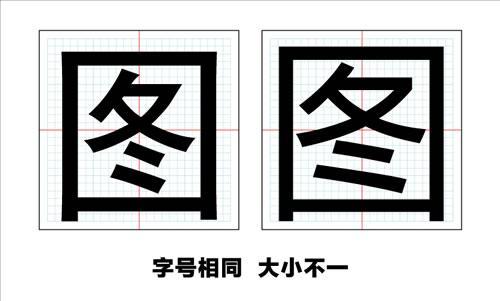
图2
字身框和字面框之间的距离就是半个自然字距。能正确地运用好他们之间的关系,是字体设计的基础。
字身字面比:“简单说就是在字身框不变的情况下,两者之间的百分比值,比值大字就大,比值小字就小,说白了就是把字放大和缩小。”
图3
现在有许多用户,为了能挤排,图省事,不惜把字缩小,造成字与字距之间的关系失衡。这样使用,即使有再好的字体也排不出完美的版面来,这是非常不科学的用法,与其这样,还不如缩小字号来用显得完美。
3. 字面的可测量大小和视觉大小
字面大小又可分为可测量的字面大小和视觉上的字面大小。已故字体设计大师谢培元老师在1962年归纳总结的“第二中心线”理论已表明,汉字由形声组合的字都是可以测量的,形旁和声旁这两个部件的中心距离越大,字面就越大,反之,字面就越小,我们只要测量这两个部件的中心距离就可以得到相应的字面大小值。同时,这也是控制整副字大小的有效工具。
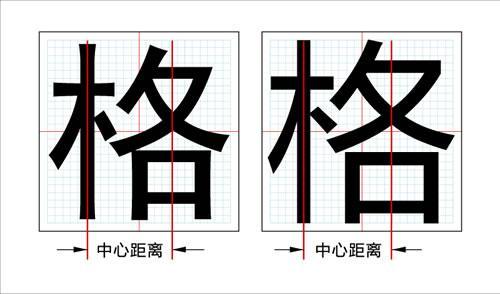
图4
雅黑在保持文字个性的基础上,尽可能的扩大形声这两个部件的中心距离来增大字面。同时,运用这种方法使得80%以上的字,大小保持一致。对于那些不能测量的字和一些易见小的字,雅黑又是如何处理呢?
字如从几何形角度来看,汉字形状众多,最典型的可分为四种类型:“方形、圆形、三角形和菱形”,从面积上看方形最大,菱形最小,要想把图形面积变得一样大小,就必须按菱形大小走,这样设计出的汉字才能在视觉上保持一致。
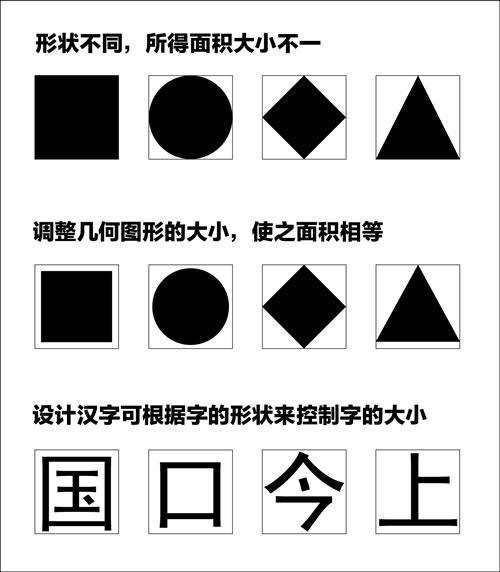
图5
要想做大字面的字,我们首先要考虑面积最小的菱形,那么,怎样才能把菱形字做大?很简单,只要适当调整改变菱形的形状,那么,我们就能得到比原来菱形面积大的形变图形,用这种方法来设计,就可以得到在视觉上比原先字面大的字。
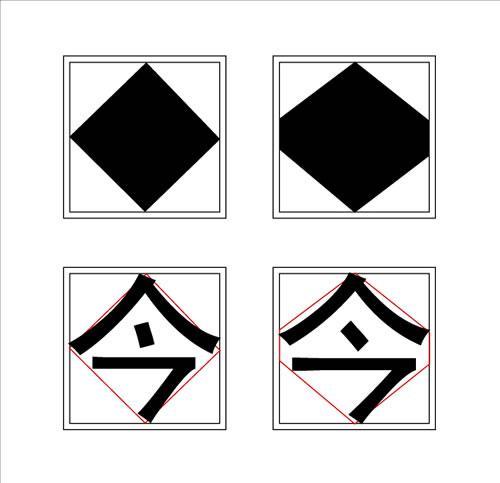
图6
雅黑在设计初期就是用视觉大小这种方法来定字面大小的。
4. 字面大小和屏幕显示的关系
字面大小和屏幕显示又有什么关系呢? 为了说明问题,用少点阵图来比较说明。
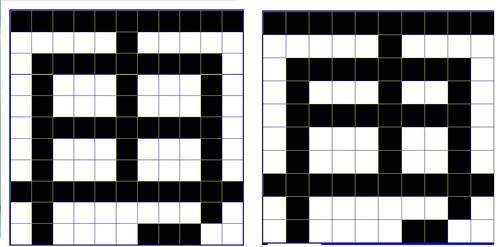
图7
从上面两图比较中我们可以看出,左图字面大,占像素多,内白均匀舒适、清晰易读。右图字面小,占像素少,因此,内白不匀称、识读效果变差。
雅黑设计时考虑到这一因素,不但采用大字面设计,同时,在字距较合理的范围内调大了字身字面,多争取到了每一点宝贵的像素,为小字号使用的清晰易读奠定了基础。
5. 去掉影响屏幕显示效果的“喇叭”口
现用黑体字的笔锋过大,成喇叭状,我们戏称为“喇叭头”或“喇叭口”。传统手写的黑体本应没有这么大的“喇叭头”,只稍微有点笔锋。那么,这“喇叭头”又是从何而来?有两个原因,第一,可能是个别写字人员认为喇叭口稍大些精神,故意写大些,第二,在把照相字模版的字翻制成电脑字库时,做字人员在不明白黑体字应有笔型的情况下,把原本制作照相字模版时,为防止在拍照缩小的过程中笔划变得虚弱、变圆走型而装上的“小辫”给融进了笔划,形成现在这样的“喇叭口”。
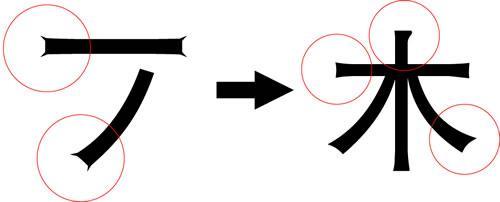
图8
过大的喇叭头,不但失去了黑体字应有的品格,在屏显时,“喇叭头”能在笔划两头多出一块,如果两笔离得较近,头就有可能连上,使笔划交代不清,可读性变差。
图9
雅黑属无装饰风格的字体,少了不必要的累赘,自然避免了这类问题的出现,使文字清晰易读。
三.雅黑设计中的要点
1.雅黑是根据我在90年代初期设计的黑体字库系列样张改进设计的。
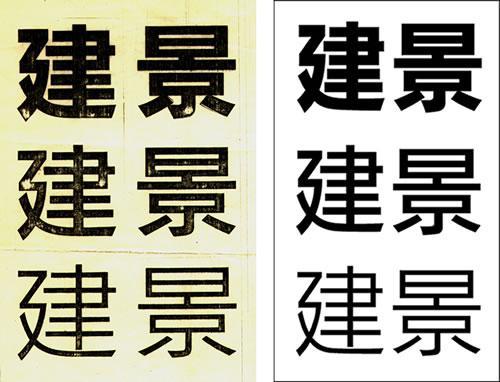
图10
从上述样张中可以看出,字体符合屏显字体的基本要求,字面大,无“喇叭头”,属无装饰风格的字体,可以作为雅黑的设计基础来改进提高。
2.雅黑设计上主要改进了字的粗细,“钩”的僵硬和“八”字点的写法,使其符合规范要求。同时,更注重线条的刻画,使其柔和挺拔富有弹性。
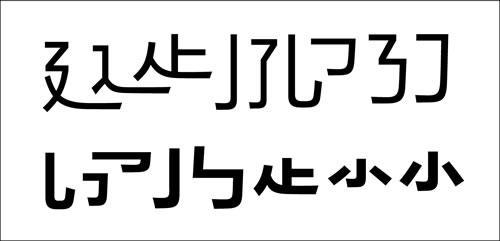
图11 部分笔划笔型图
3.为了使正文字的阅读效果更好,对所有的口和带框的部件加“脚”,也就是口下面出头,其目的是为了给眼睛以适量的刺激,来提高阅读速度,这是正文用雅黑设计的一次新尝试。
图12 口和带框的部件加“脚”
4. 为适合屏幕显示用,在字结构的处理上“计白当黑”,严格控制“白”在各部位所占的比例,使其舒朗匀称。
图13 黑白处理示意图
这种处理方式不但使字稳重大方,而且使字撇捺舒展、飘逸潇洒、富有姿态。
5. 采用独创的手法对笔划进行特殊处理,减少交错连笔处的黑度,使字的整体灰度更好,更清晰,更适合屏显。
图14 特殊笔划处理示意图
6.避免笔划交代不清,粘连过多
图15
这些字笔划交代不清,粘连过多,既降低了识、读的速度,又有错字嫌疑 。雅黑在设计时就尽量避免这种问题的发生。
图16
四.笔划粗细与结构、留白、重心之间的关系
这是活字设计中的一个综合问题,并非一朝一夕就能掌握的,它不但对字的个性要有深刻的理解,而且还要具有非常敏锐的观察力。做字的过程其实就是练眼的过程,眼睛练“凶”了,字自然越做越好。
下面通过调整统一字体的粗细,来了解笔划粗细与结构、留白、重心之间的关系。为了更好的说明问题,便于理解,选用多笔划和少笔划的粗体字为例。
图17
1 调整字的粗细,使之成为一个整体
这两个字一粗一细,视觉上看是两款字,粗细调整不当。首先,把细的“體”字加粗,使两个字的视觉粗细一致。
图18
2 字的内白影响字的重心
“體”字在加粗后,虽然在粗细上合适了,但是,看着还不舒服,仔细分析一下原因,问题在于内白,各部件的重心位置欠妥,骨字重心偏高,曲、豆重心偏低,使得互相间的呼应性、协调力变差。那么,我们只要调整“體”字的内白,改变重心位置就行。
图19
3 调整字的局部粗细来改善字的结构,提高字的品位
现在我们来调整“粗”字,先分析一下粗字的那些地方需要改进,米字过大过黑,形象欠佳并压迫且字,从而使结合部太紧,整字见窄。改进的方法是:缩小米字,放大且字,减细米字上方的八字点,改善横眉竖眼的“凶”相并使点见长,加长撇梢,使其舒展,分清下点使其交代清楚。通过这些调整,粗字变得面貌一新,提高了品位。
图20
“粗體”两字通过调整粗细、内白,改变重心与结构,使“粗體”两字变得更完美。
图21
从上面的几次调整中可以看出,笔划粗细与结构、留白、重心之间是相互相成的关系,是一个不可分割的整体,只要协调好它们之间的关系,就能提升字的品格,并有良好的排版效果。
雅黑在设计制作过程中就是运用这种设计技巧使字既有品位,又整齐划一,灰度良好。
五.文字的形象、表情与气质
笔型是构成文字笔画、风格的基本元素,笔画制作的完成度会影响到成字后字的品质,而字的结构就好比人体的比例、五官的位置,它直接能体现文字的形象、表情与气质。因此,对于字体设计制作来说,每一环节都是至关重要的。我们设计黑体字,要表达出黑体字本身具有的庄重、典雅的特性,就必须先把笔划做好,把字写端正。
图22
从上面这些字我们可以看到,这些字就没有写端正,笔划生硬,制作粗糙,部件之间的位置安排欠妥。大头小头缩头,重心有高有低,结构松散,整体形象不好,给人以不整齐、不稳重的印象,缺乏正气感。下面雅黑的感觉就比较整齐舒适。
图23
我们再来具体的对比分析一些字的常见病例。
1. 笔划僵硬,制作粗糙,严重影响字的品质。
图24
2. 撇捺不舒展,使字失去应有的姿态。
图25
3. 缩头
图26
点划的头已伸不出去,还要斜,既不美观,又破坏形象。在头见短,伸不出去的情况下,还是做的稍平些比较妥当,头也长了,字也显得正气。